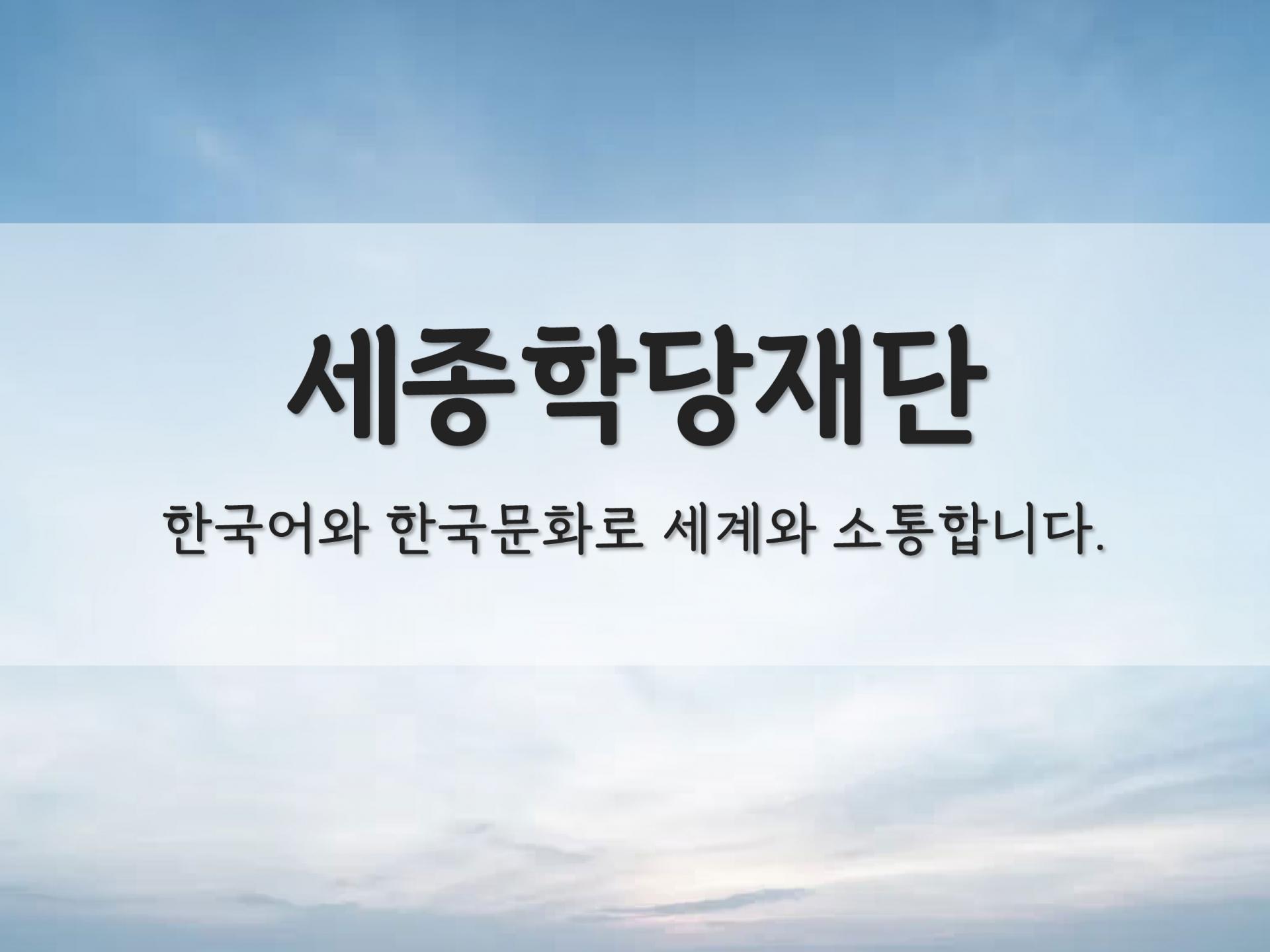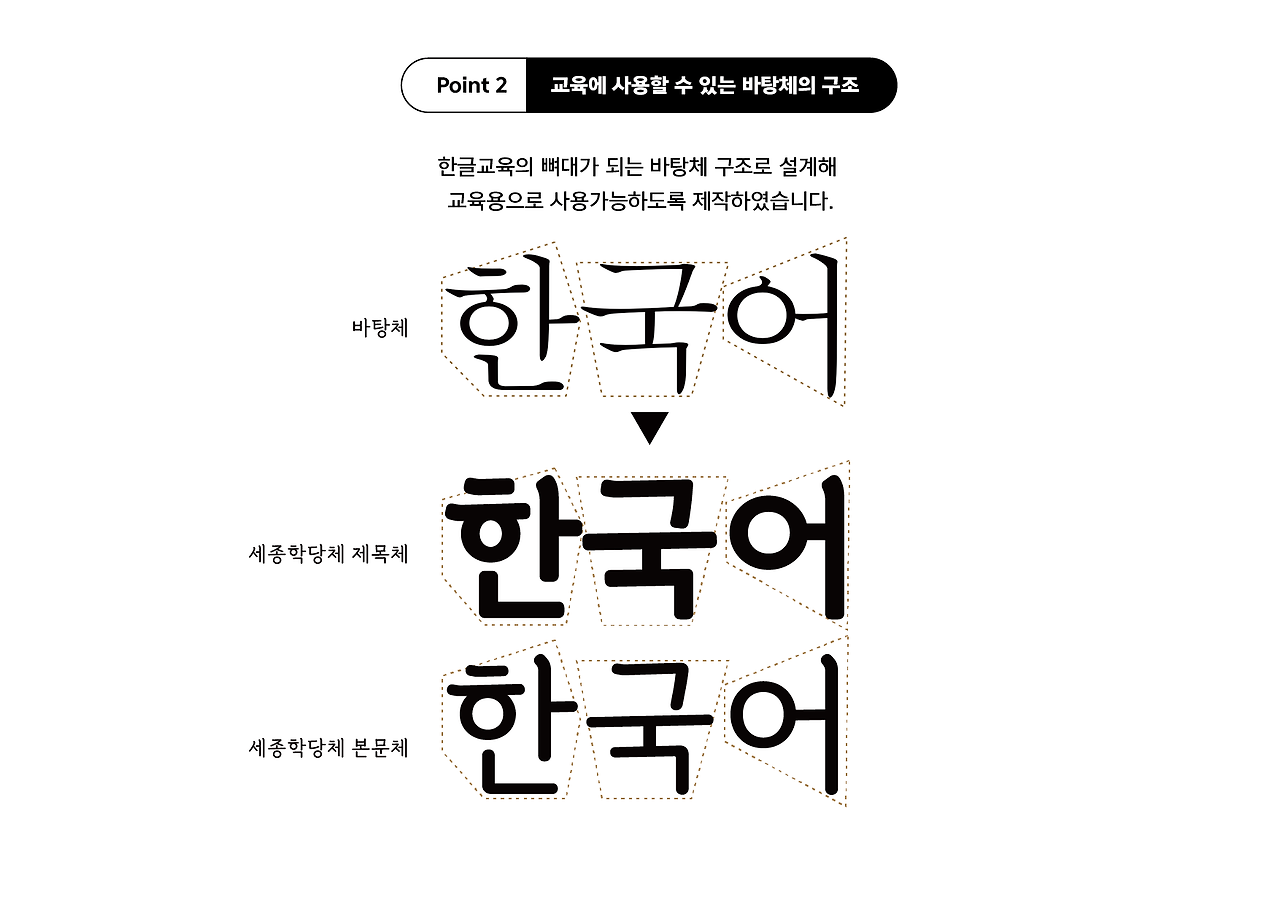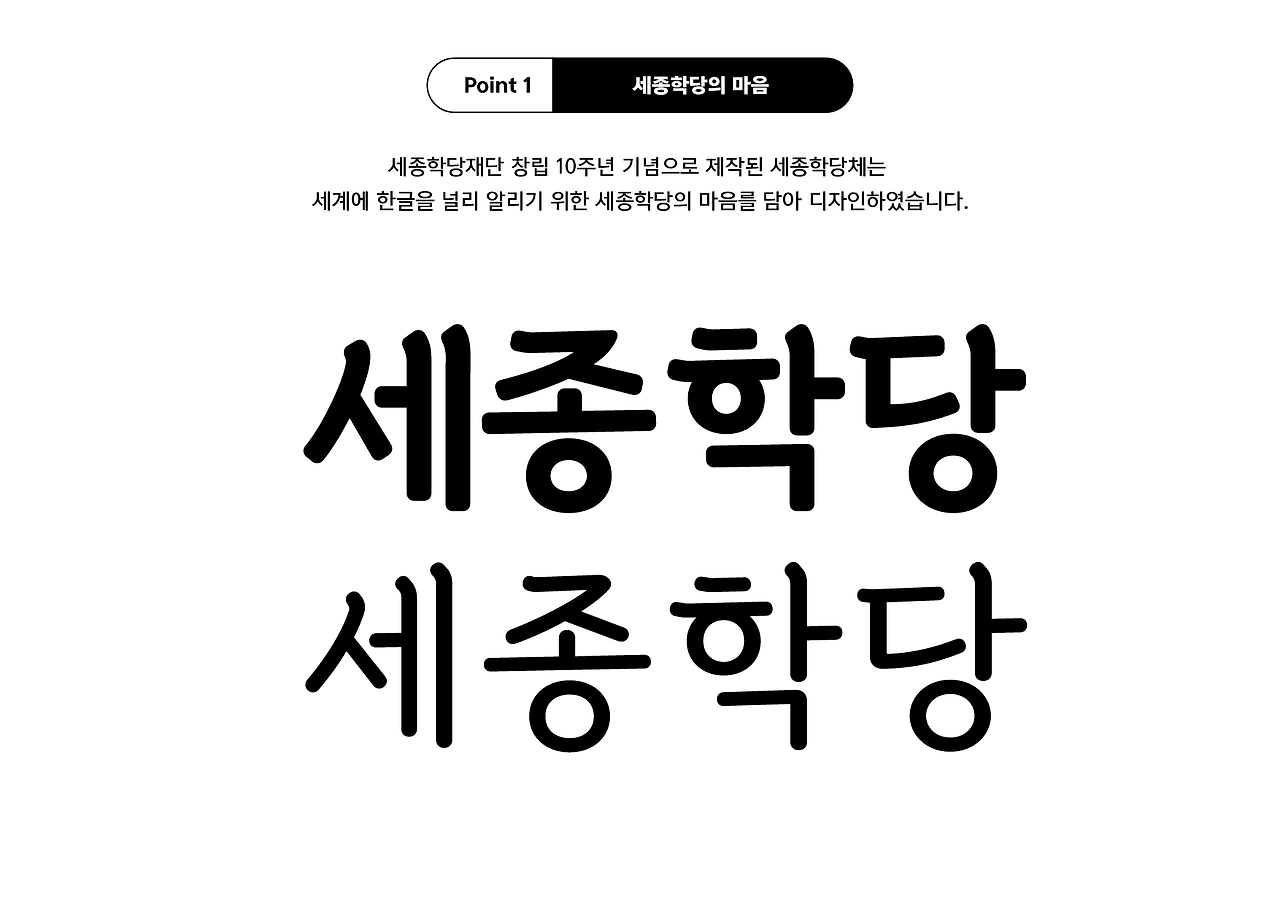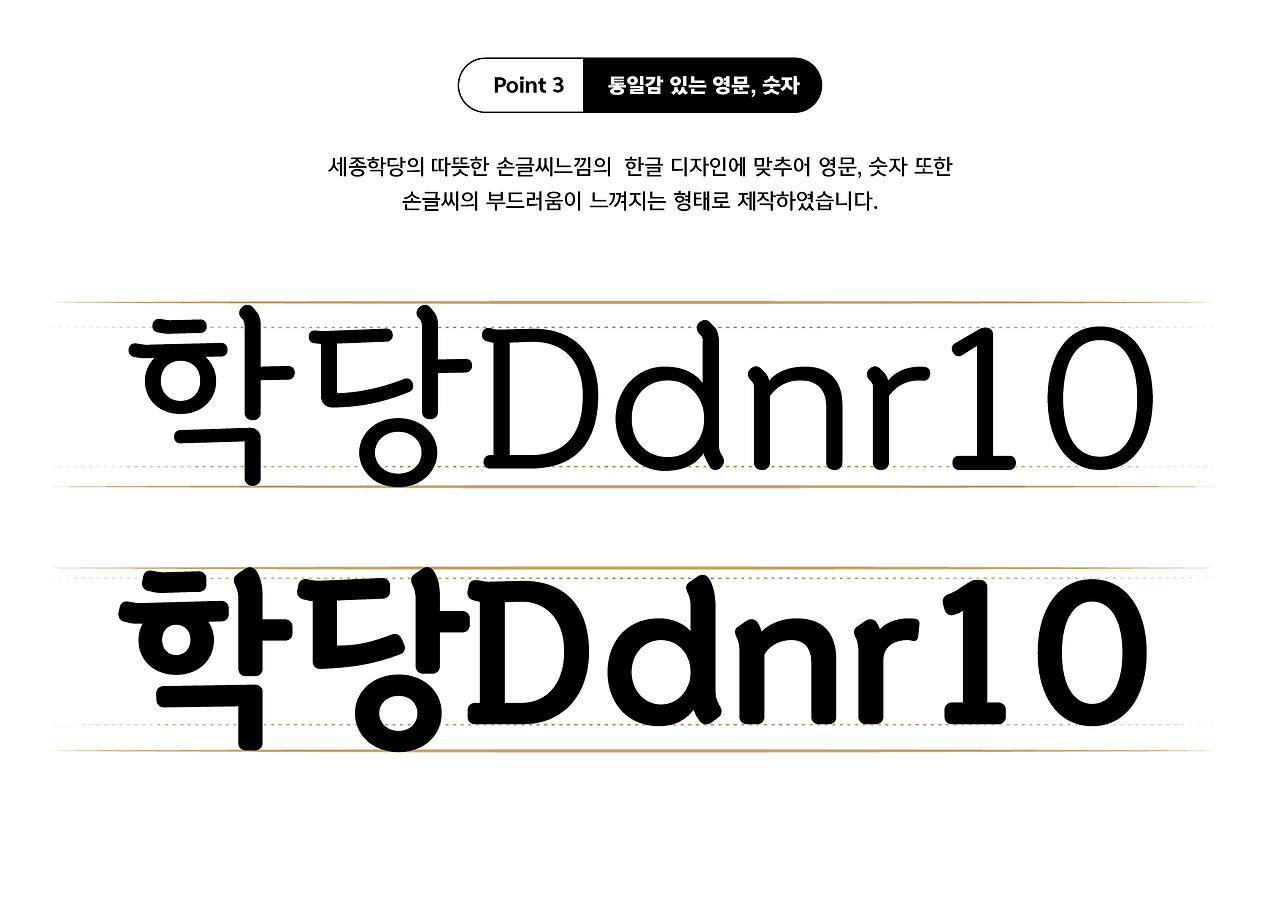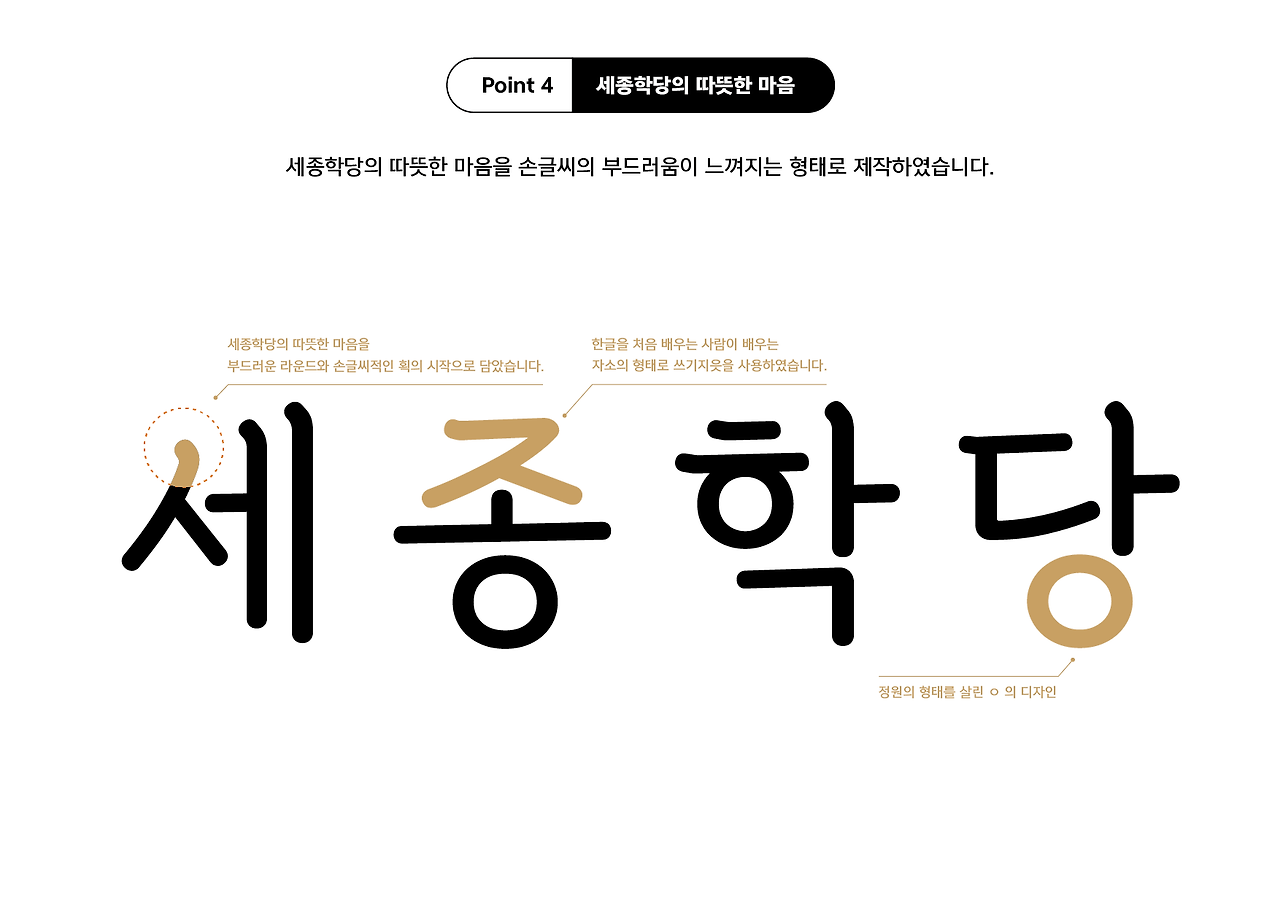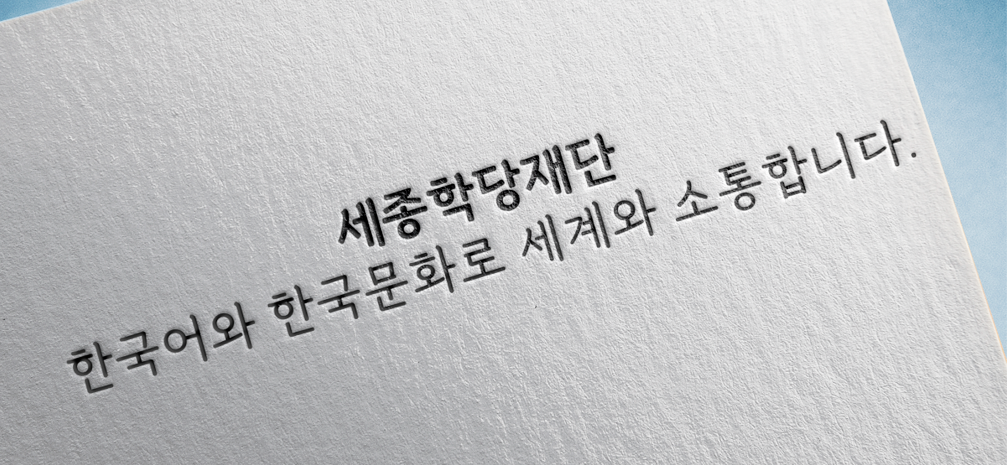
세종학당재단 [세종학당체]
세종학당재단 창립 10주년 기념으로 제작된 세종학당체는 세계에 한글을 널리 알리기 위한 세종학당재단의 마음을 담아 디자인했다. 한글교육의 뼈대가 되는 바탕체 구조로 설계하여 교육용으로 사용가능하며, 손글씨의 따뜻한 느낌을 부드러운 획의 굴림과 인상으로 더했다.